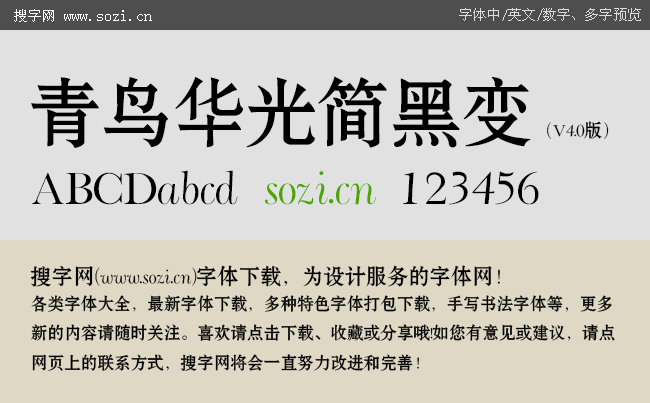
青鳥華光簡(jiǎn)黑變
搜字網(wǎng)提供一款青鳥華光簡(jiǎn)黑變中文字體下載,青鳥華光簡(jiǎn)黑變是一款簡(jiǎn)潔端正的宋黑字體,該字體形體方正,筆畫簡(jiǎn)潔,可用于報(bào)刊雜志排版,也適用于平面廣告,圖書印刷等廣告設(shè)計(jì)場(chǎng)合使用。